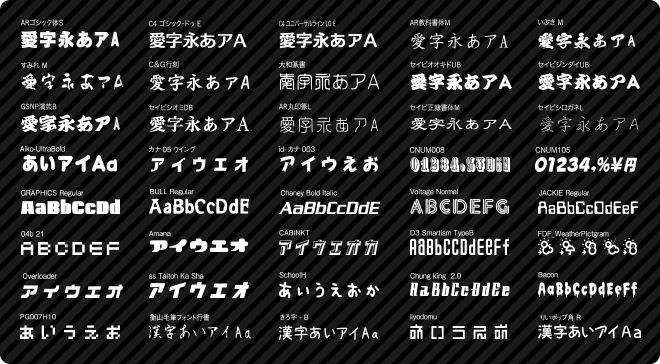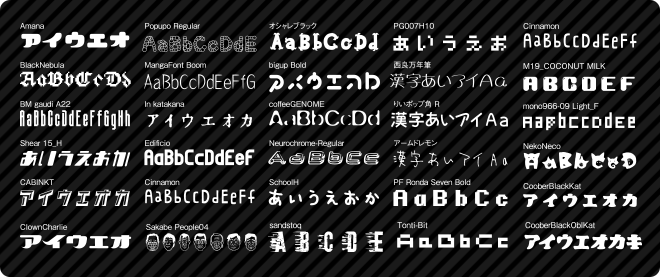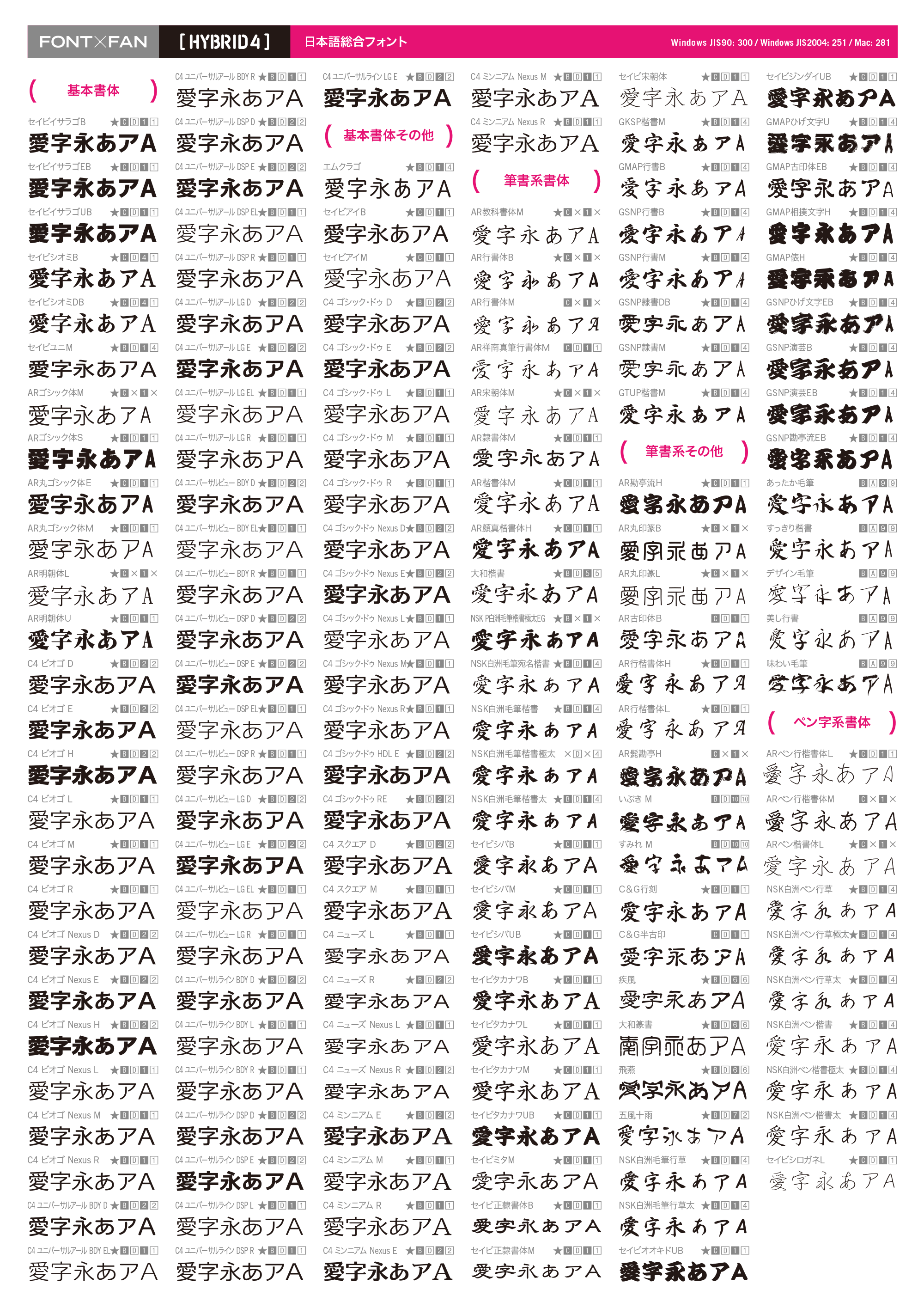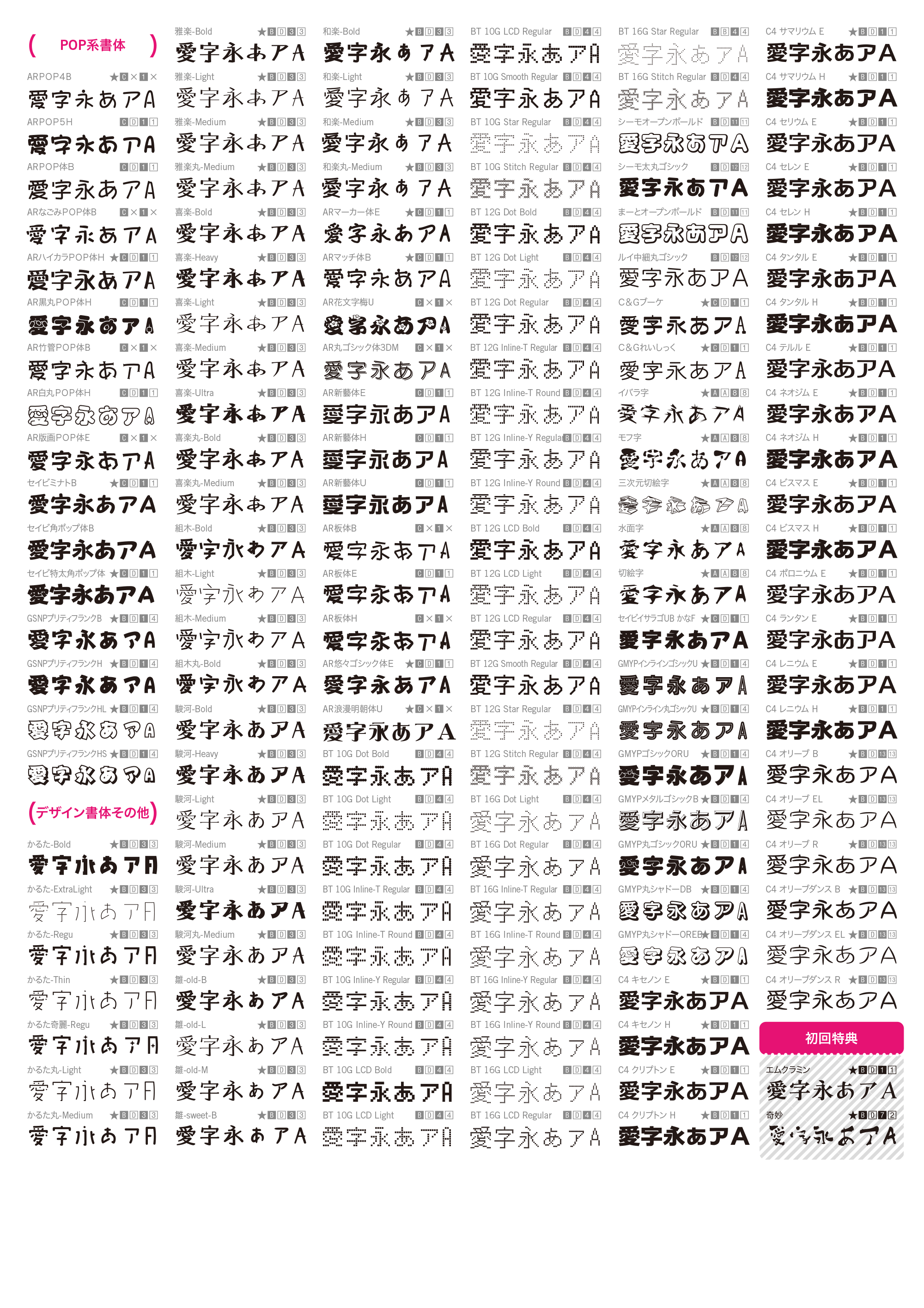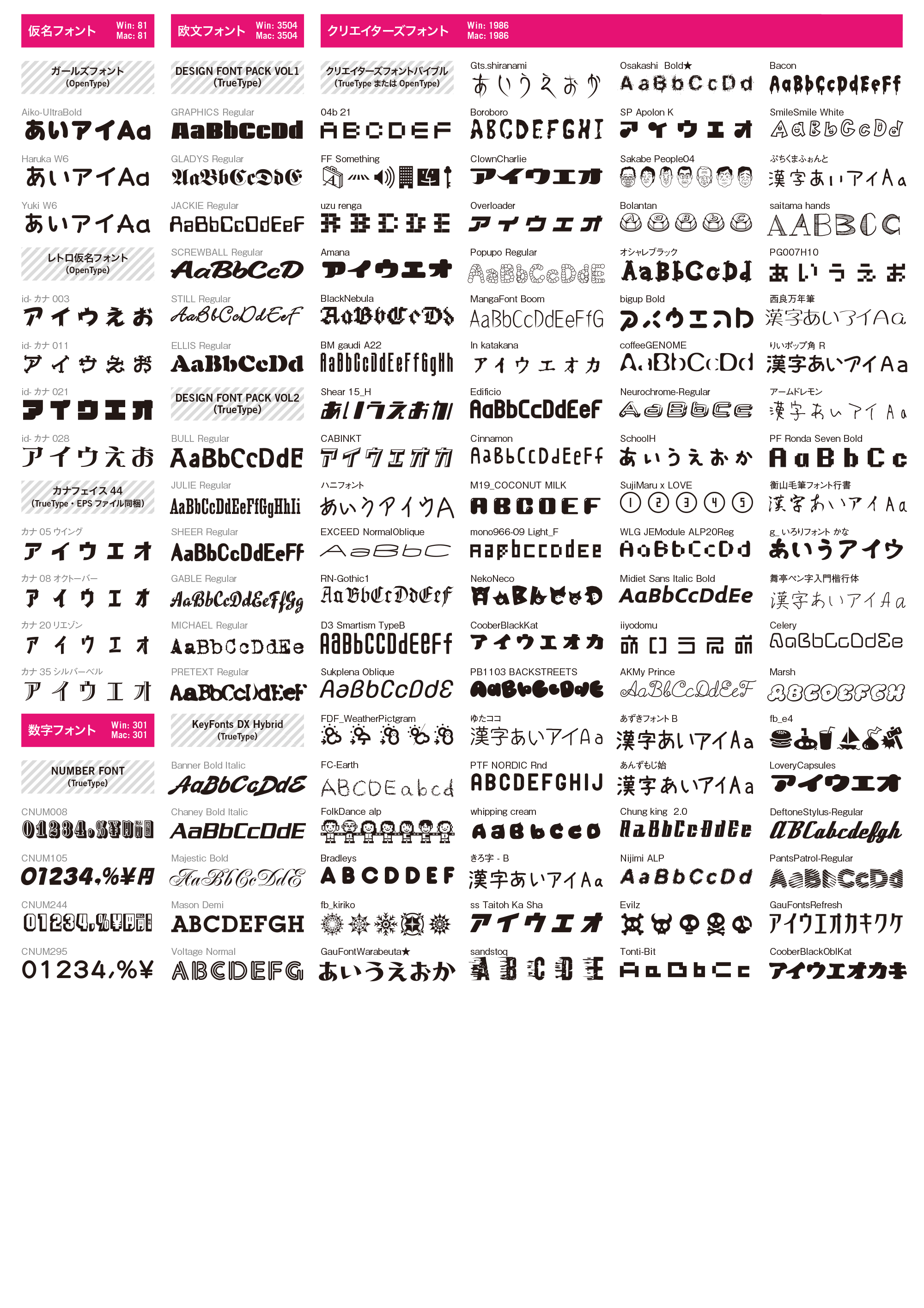
FONT×FAN HYBRID 4(フォントファン ハイブリッド 4)
個別のフォント製品や日本語総合フォント製品を多数収録。
国内最大級となる12,576のフォントを収録、年間ライセンス製品ものはもちろん売り切り型のフォント製品の中でも最大規模の収録となります。
前作より更に日本語総合フォントを追加し、クリエイターズフォントも6ブランド206フォントを追加収録。クリエイターズフォントは未公開フォント、限定フォントや日本語フォントも多数収録されています。
初回特典としてFANプロデュースブランド『空草字房』の一般初公開フォント『奇妙』と新ブランド『エムフォント』の第2弾フォント手書き風のクラシカル明朝『エムクラミン』を特別収録。
Windows用日本語フォントにはWindows用文字セットCP932(マイクロソフト標準キャラクタセット)という文字セットがあります。
この文字セットはJIS第一水準、第二水準を含むJISX0208:1990(以下、JIS90)の規格が含まれます。 WindowsではWindowsXPまでこのJIS90字形を採用しており、その他Macや携帯電話など多くのコンピューターや端末機器でJIS90字形が採用されており今も主流となっております。
WindowsVista以降マイクロソフト社はシステム標準フォント(MSゴシック、MS明朝、メイリオ)にJISX0213:2004(以下、JIS2004)の規格を採用した結果、重複する文字コードでもJIS90とは一部字形が異なることになり、両方の字形が混在しているのが現状です。
結果、WindowsVista以降のユーザまたはJIS2004字形のフォントを利用しているユーザとJIS90字形を利用しているユーザ間での文書やメールでやり取りにおいて、送る側と受け取る側で一部字形が異なるという場合があります。
一般の個人利用等ではこの字形の違いで困る場面は少ないと思われますが、業務利用等において使用する字形が指定されている場合は、この字形の違いが存在することを意識して利用する必要があります。
なお、マイクロソフト社ではシステム標準で付属するフォントとは異なるJIS90またはJIS2004字形のシステムフォントも入手できるよう対応が行われています。
本製品のWindows版はJIS90字形またはJIS2004字形のフォントが収録されておりますので用途に合わせてご利用ください。Mac版は基本的に全てJIS90字形です。
JIS90とJIS2004で異なる字形の167字一覧表 [※クリックで拡大]
※重複する文字コードにおける第一水準および第二水準の文字が対象です。
※表示の文字はMS明朝を使用して表示しているものであって、JISで規定される文字での表示ではありません。